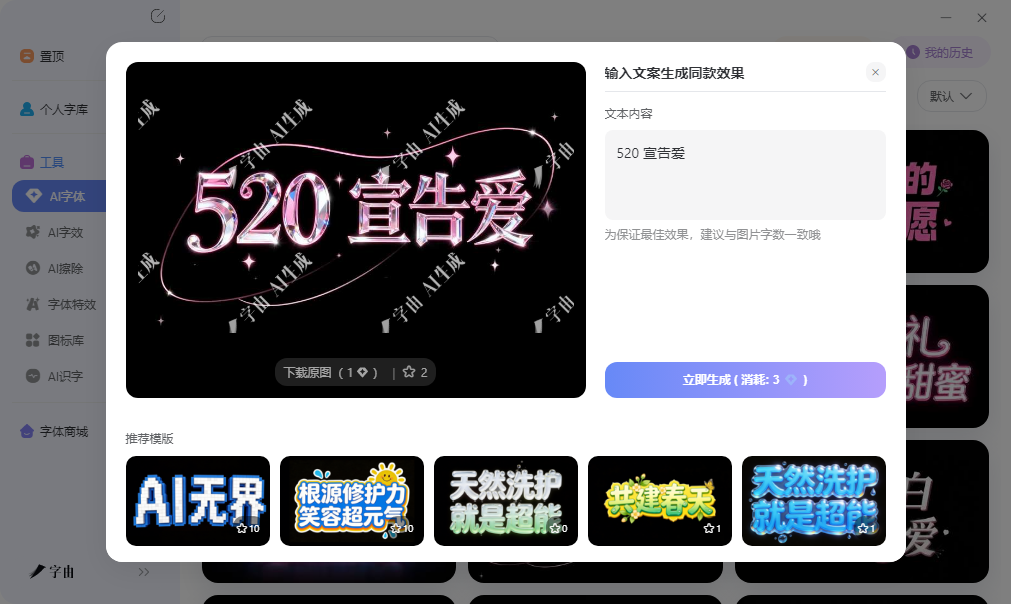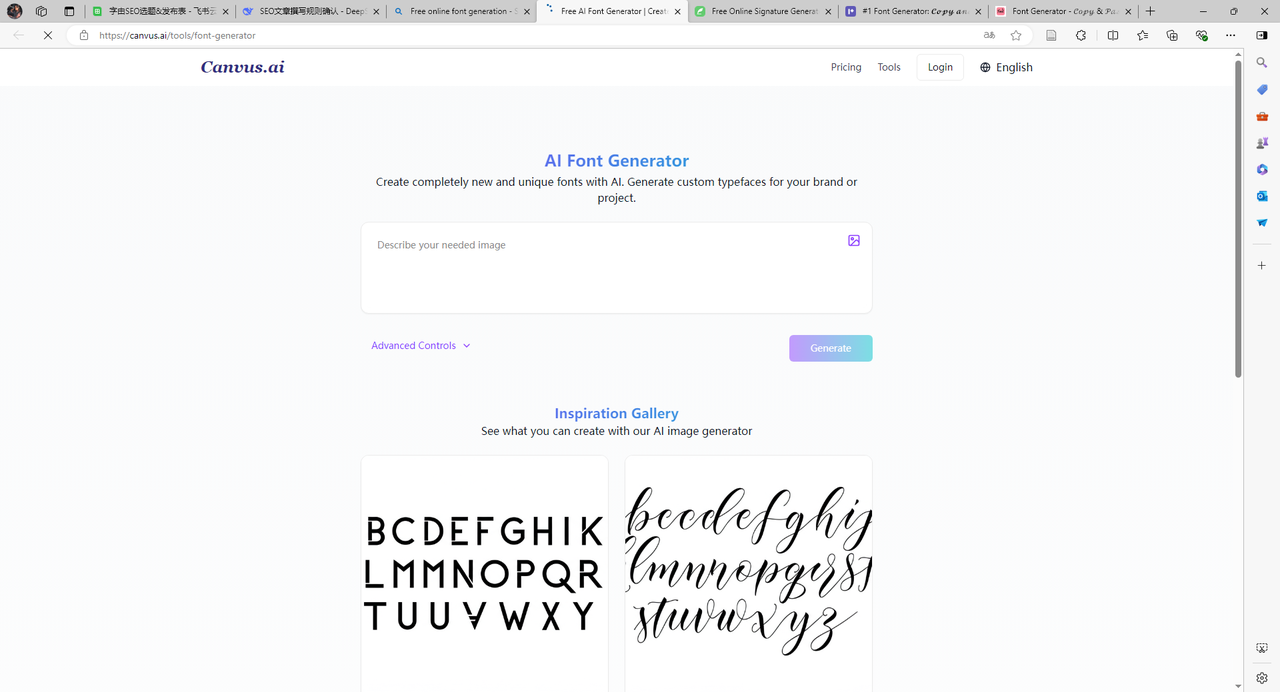
免费字体在线生成工具,几分钟搞定个性文字
做海报标题、品牌Logo或社交媒体配图时,普通字体不够个性。现在有不少免费在线工具,输入文字就能生成艺术字图片,或转换成花式字体复制粘贴。这篇文章测试了5款工具,有的提供现成模板直接套用,有的通过文字描述生成定制字体,还有的支持一键复制花式字体到社交平台。操作难度和输出格式不同,可以根据自己的需求来选择。
字由的AI字体功能内置了超过400种文字特效模板。这些模板按照设计风格分组,每组风格下有几十款具体样式。每个样式已经预设了使用的字体、文字特效(如发光、阴影、渐变)、排版布局以及背景配色。用户不需要手动调整任何参数。
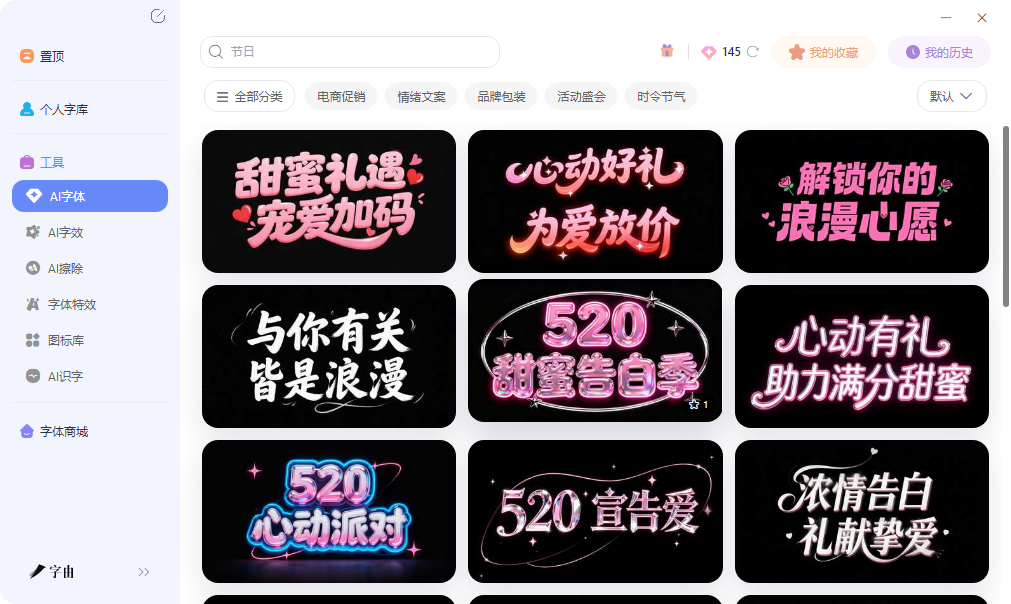
使用流程:打开字由客户端,进入AI工具区域。在左侧分类栏中选择一个风格分组,右侧会显示该分组下所有模板的缩略图。将鼠标悬停在缩略图上,预览区会动态显示用户输入的文字效果。用户在上方输入框中填写自己的文案,点击缩略图下方的生成按钮。系统处理时间约10到15秒,完成后输出一张分辨率为2K级别的PNG图片。图片背景为透明,可直接拖入Photoshop、Canva或剪映等软件中使用。
2、canvasai
第二个工具是AI Font Generator。用户不需要从现成模板中选择,而是通过文字描述想要的效果,AI根据描述生成全新的定制字体。
操作方式:用户打开网页,在输入框中填写描述文字。描述可以包括字体风格、笔画特征、应用场景等信息。例如“一款粗壮的工业感无衬线体,笔画方正,适合机械品牌Logo”。填写完成后点击Generate按钮,AI输出一套完整的字体家族预览,包括大写字母、小写字母、数字和常用符号的样式。页面还提供Advanced Controls(高级控制)和Inspiration Gallery(灵感画廊),用户可以查看示例作品获取灵感。
定制流程:的生成流程分为几个步骤。第一步是描述需求,用户可以用自然语言描述想要的字体特征。第二步是AI生成预览,系统会根据描述生成字符集预览图。第三步是调整优化,如果用户对某些字符不满意,可以通过高级控制进行微调。第四步是导出字体文件,确认所有字符符合要求后,用户可以下载TTF或OTF格式的字体文件,安装到电脑中使用。
3、CocoSign
第三个网站是CocoSign的Signature Generator。它主要用于生成电子签名,支持打字签名和手绘签名两种模式。用户在上方输入框中输入自己的姓名,从字体下拉菜单中选择字体(如Dancing Script),调整字体大小(48px)、颜色、背景(支持透明),设置签名倾斜度(Slope)和倾斜角度(Slant)。设置完成后,系统实时显示签名效果。用户点击Save保存签名图片。用户可以使用鼠标或触控板在画布上手写签名。系统会保留笔迹的原始轨迹,用户可以调节笔触粗细和颜色。手绘完成后保存为图片,用于电子合同或邮件签名。
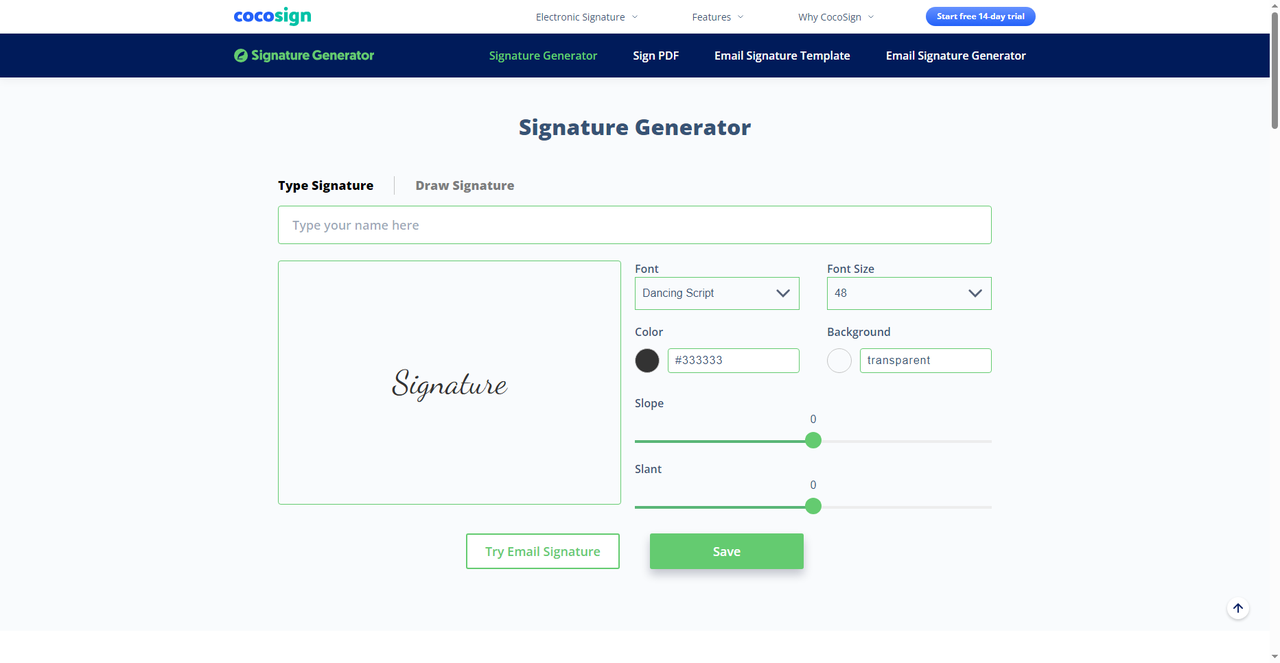
4、Pixelied
第四个网站是Pixelied的Font Generator。用户输入文字后,系统提供多种花式字体样式,包括Glitch(故障体)、Small(小型大写)、Fancy(花体)、Cursed(诅咒体)、Tattoo(纹身体)、Bold(粗体)、Curse等。每种样式下方有Copy按钮,点击即可复制转换后的文本。Pixelied还提供了Instagram预览功能。页面右侧模拟了Instagram个人主页的预览效果,显示头像、帖子数、粉丝数、关注数等信息。用户输入的文字会被应用到预览中,帮助用户直观了解字体在社交平台上的显示效果。这个功能对于运营社交媒体的用户非常实用。
用户需要在Instagram、TikTok、Twitter等社交平台发布花式文字。用户想要快速预览字体在社交平台上的效果。该工具完全免费,无需注册,输出的是Unicode字符,接收方不需要安装任何字体。
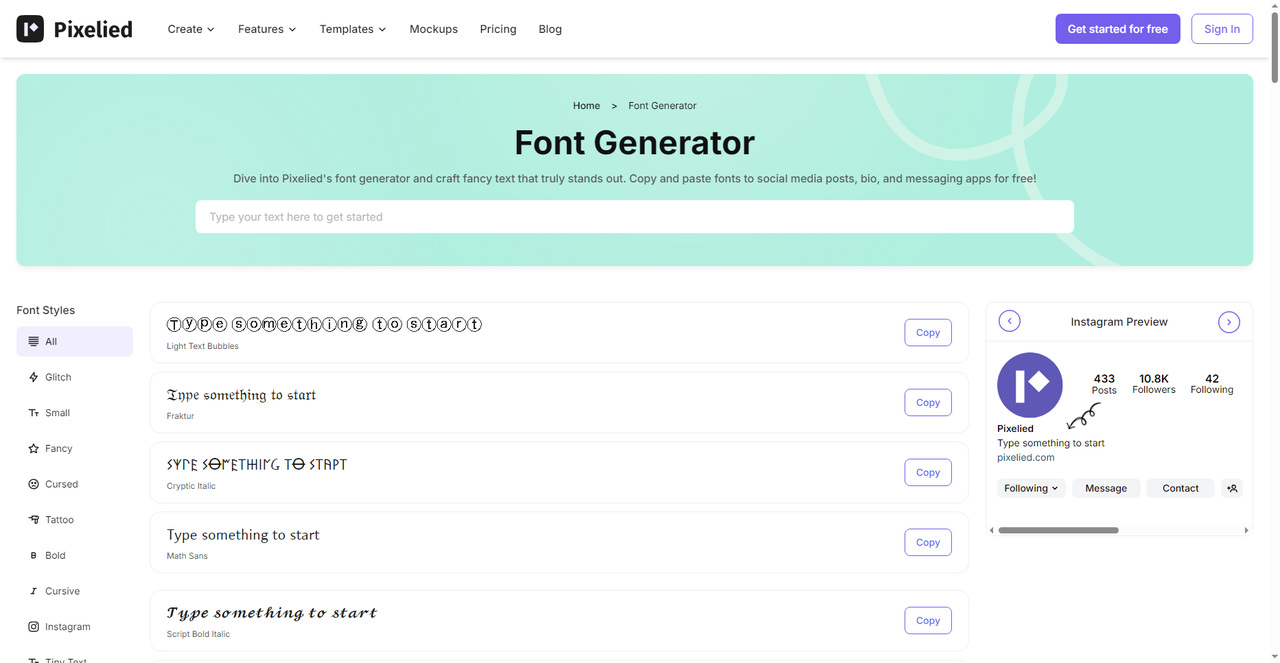
5、Font Generator
第五个网站是一个通用的Font Generator。用户输入文字后,系统可将其转换成150多种花式字体样式。页面提供搜索框,用户可以按样式名称搜索(如Cursive、Bubble、Gothic)。每种样式显示预览效果,旁边有Copy按钮。页面顶部显示当前字符数量(Character Count),帮助用户控制文案长度。该工具的花式字体覆盖了草书、气泡体、哥特体、双线体、粗体、斜体、小型大写等多种风格。用户无需注册,完全免费。
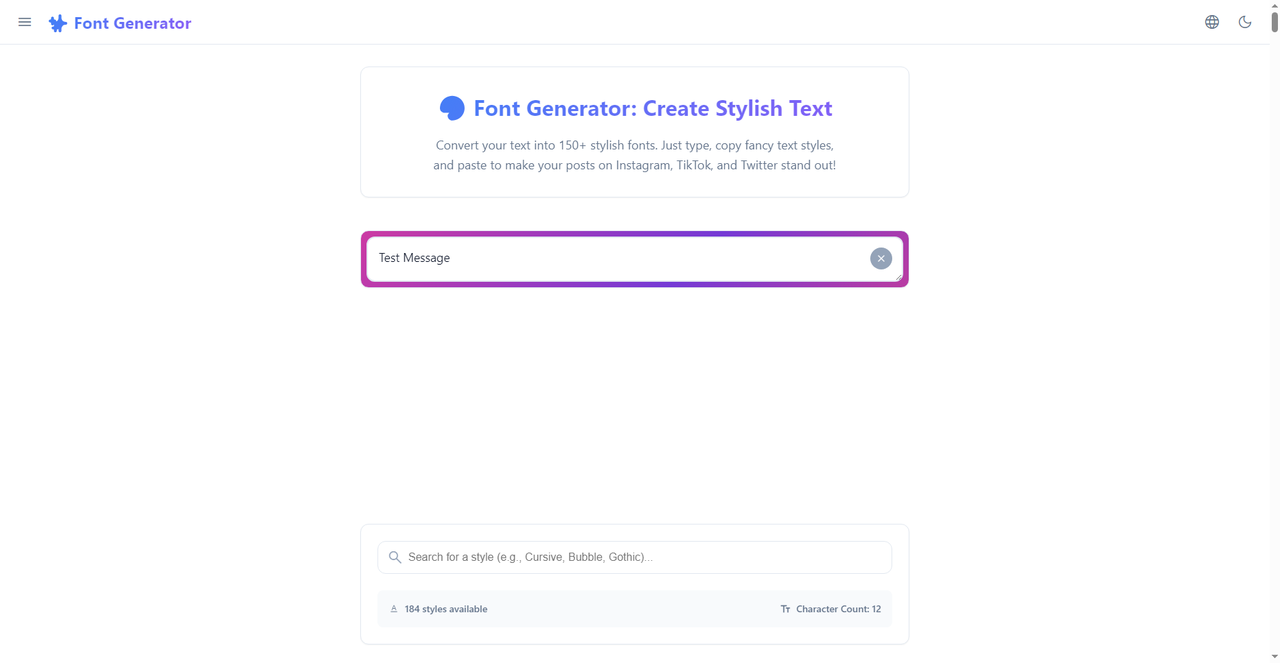
输入文字,选一个工具,几分钟拿到结果。字由的AI字体功能在客户端里直接出图,每天免费点数够日常用。canvasai适合有明确想法但找不到现成模板的人,写一段描述让AI生成。CocoSign专做电子签名,打字或手绘都行。Pixelied和通用Font Generator负责花式文本,复制粘贴到社交平台。不用纠结哪个最好,根据手头是什么活选就行。要海报标题用字由,要独家字体用canvas,要签名用CocoSign,要发朋友圈用后两个。免费、在线、不用学。